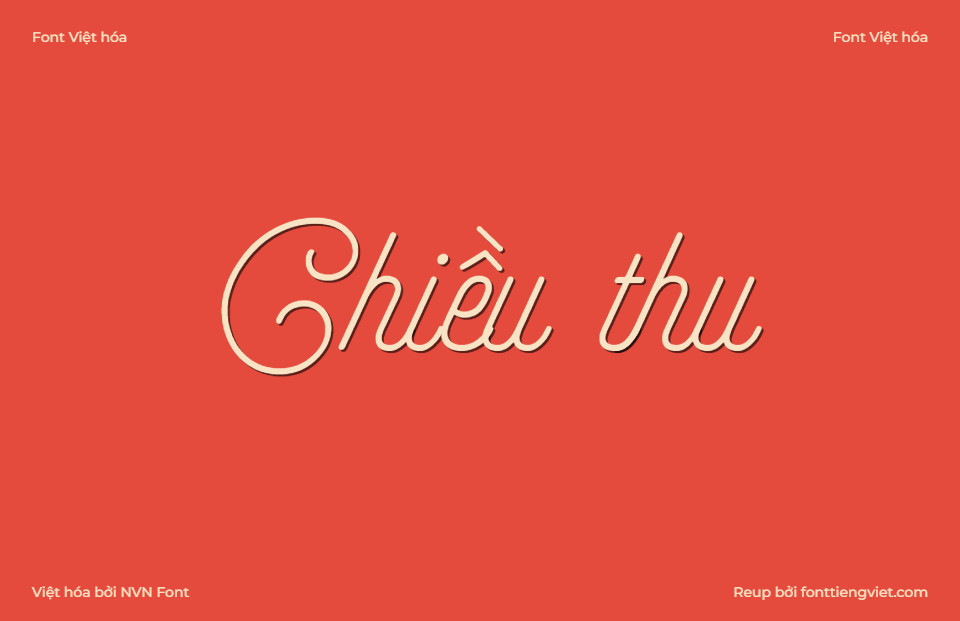
Font Việt hoá NVN Selfie Regular
Font Việt hoá NVN Selfie Regular – Lựa chọn hoàn hảo cho thiết kế trẻ trung và hiện đại
Giới thiệu về Font Việt hoá NVN Selfie Regular trong thiết kế đồ họa
Trong thế giới sáng tạo đầy màu sắc, việc lựa chọn một bộ Font Miễn Phí chất lượng đóng vai trò quyết định đến sự thành công của một sản phẩm truyền thông. Font Việt hoá NVN Selfie Regular là một bộ phông chữ thuộc phong cách Script hiện đại, được lấy cảm hứng trực tiếp từ những tấm bảng hiệu cổ điển tại Buenos Aires. Với các đường nét thanh mảnh, uyển chuyển nhưng vẫn giữ được sự chắc chắn, bộ font này nhanh chóng trở thành công cụ đắc lực cho các bạn học sinh, sinh viên và giáo viên trong việc thiết kế slide bài giảng hay thiệp mừng. Điểm đặc biệt của phiên bản này chính là sự tỉ mỉ trong quá trình Việt hóa, giúp người dùng gõ tiếng Việt có dấu một cách mượt mà mà không lo gặp lỗi hiển thị hay lỗi font hệ thống thường thấy.
Đặc điểm nổi bật của bộ Font Việt hoá NVN Selfie Regular
Bộ phông chữ này sở hữu cấu trúc hình học cân đối, giúp tạo nên một cảm giác ngăn nắp nhưng không kém phần nghệ thuật. Từng nét chữ trong Font Việt hoá NVN Selfie Regular được chăm chút kỹ lưỡng để đảm bảo tính dễ đọc trên cả thiết bị di động lẫn bản in. Khác với những bộ font Script rườm rà, Selfie Regular giữ được sự tinh tế tối giản, làm cho nội dung văn bản trở nên thanh thoát và gần gũi hơn với người xem. Điều này đặc biệt phù hợp cho các chủ đề về đời sống, thời trang, du lịch hoặc các dự án nghệ thuật của nhà trường. Khi sử dụng bộ font này, bạn sẽ thấy các ký tự liên kết với nhau rất tự nhiên, tạo ra một dòng chảy thị giác lôi cuốn, giúp thông điệp truyền tải trở nên ấn tượng hơn bao giờ hết trong mắt người đối diện.
Ứng dụng thực tế của Font Việt hoá NVN Selfie Regular
Nhờ vào phong cách thiết kế độc đáo, bộ phông chữ này có tính ứng dụng cực kỳ linh hoạt trong nhiều lĩnh vực khác nhau. Đầu tiên phải kể đến là mảng thiết kế thương hiệu và bao bì sản phẩm, nơi đòi hỏi sự sáng tạo và cá tính riêng biệt. Các bạn học sinh cũng có thể sử dụng Font Việt hoá NVN Selfie Regular để làm tiêu đề cho các báo tường, tập san hoặc trang trí ảnh kỷ yếu. Trong môi trường sư phạm, giáo viên có thể dùng nó để tạo ra các chứng nhận khen thưởng hoặc các thiệp mời họp phụ huynh để tăng thêm phần trang trọng và ấm cúng. Ngoài ra, phông chữ này còn rất được ưa chuộng trong việc thiết kế các bài đăng mạng xã hội như Instagram hay Facebook nhờ vẻ ngoài thời thượng, bắt kịp xu hướng “Selfie” trẻ trung của thế hệ Gen Z hiện nay.
Cách kết hợp Font Việt hoá NVN Selfie Regular với các font chữ khác
Để tạo nên một bản thiết kế hài hòa, việc kết hợp phông chữ (pair font) là một kỹ năng quan trọng mà các bạn cần lưu ý. Font Việt hoá NVN Selfie Regular vốn dĩ đã có tính trang trí cao, vì vậy bạn nên phối hợp nó với những bộ font không chân (Sans-serif) đơn giản như Roboto, Montserrat hoặc Open Sans. Sự tương phản giữa các nét uốn lượn của Selfie Regular và sự góc cạnh của font không chân sẽ giúp bố cục tổng thể trở nên chuyên nghiệp và rõ ràng hơn. Hãy nhớ nguyên tắc sử dụng font Script cho các tiêu đề lớn hoặc câu trích dẫn ngắn, còn phần nội dung chi tiết nên dùng các font chữ tiêu chuẩn để đảm bảo khả năng đọc tốt nhất cho người xem ở mọi khoảng cách khác nhau.
Kết luận và trải nghiệm Font Việt hoá NVN Selfie Regular
Tổng kết lại, đây là một trong những bộ phông chữ đáng sở hữu nhất trong bộ sưu tập của bất kỳ nhà thiết kế không chuyên hay chuyên nghiệp nào. Sự kết hợp giữa phong cách cổ điển và hơi thở hiện đại đã giúp Font Việt hoá NVN Selfie Regular khẳng định được vị thế của mình trong lòng cộng đồng yêu đồ họa tại Việt Nam. Nếu bạn đang tìm kiếm một giải pháp để làm mới các bài thuyết trình hay dự án cá nhân của mình, đừng ngần ngại truy cập vào kho dữ liệu Font Miễn Phí, Font Việt Hóa, Font Việt hoá NVN Selfie Regular để tải về và sáng tạo ngay hôm nay. Chắc chắn rằng sự mềm mại và cá tính của bộ font này sẽ mang đến một làn gió mới, giúp những ý tưởng của bạn trở nên sinh động và giàu cảm xúc hơn bao giờ hết trong tương lai gần.